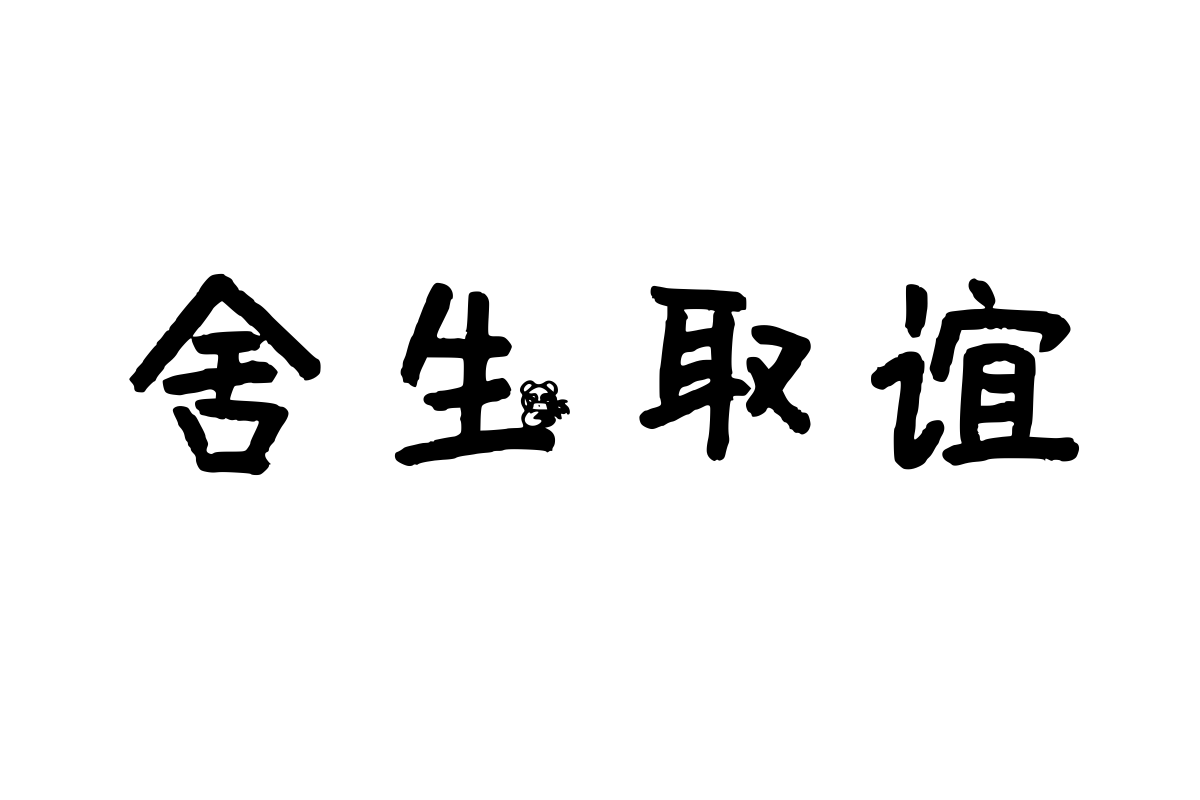
兰米熊猫宝贝字体是一款具有独特魅力的中文字体,它以可爱的熊猫为设计灵感,将熊猫的形象融入到字体中,使得整个字体充满了趣味性和亲和力。这种独特的设计让兰米熊猫宝贝字体在众多字体中脱颖而出,成为了一种独具特色的视觉体验。
兰米熊猫宝贝字体采用了圆润、饱满的字形结构,使得每一个笔画都显得非常可爱。同时,它的线条流畅自然,没有过多的装饰,给人一种简洁、大方的感觉。这种设计风格使得兰米熊猫宝贝字体非常适合用于儿童读物、卡通海报、广告宣传等多种场景。
此外,兰米熊猫宝贝字体还具有一定的可读性,无论是大字还是小字,都能清晰可见,方便阅读。同时,它的字体大小调整灵活,可以根据需要进行调整,满足不同场合的需求。
总之,兰米熊猫宝贝字体是一款非常有趣、可爱的中文字体,它将熊猫的形象与汉字相结合,为人们带来了全新的视觉体验。无论是用于个人使用还是商业用途,兰米熊猫宝贝字体都能展现出其独特的魅力。